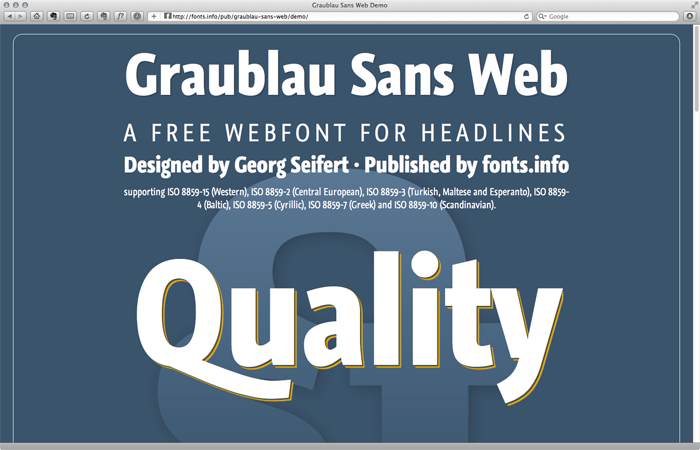
Graublau Sans Web
Die Graublau Sans Web war eine der ersten professionellen Fonts, die speziell für @font-face-Einbettung in Webseiten entwickelt wurde. Sie eignet sich insbesondere für den Einsatz in Überschriften auf Webseiten.
Georg Seifert
Das ist eine beeindruckende Schrift, die große Freude macht und dennoch klar und pragmatisch ist.